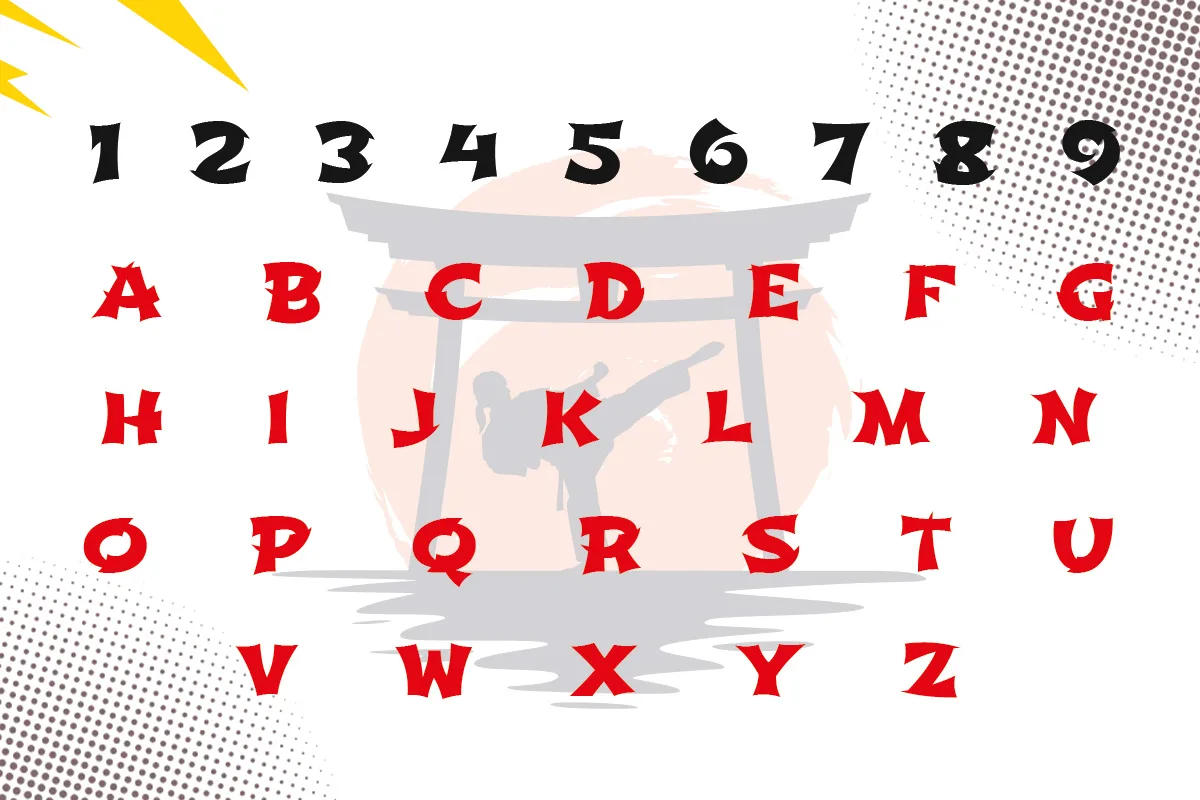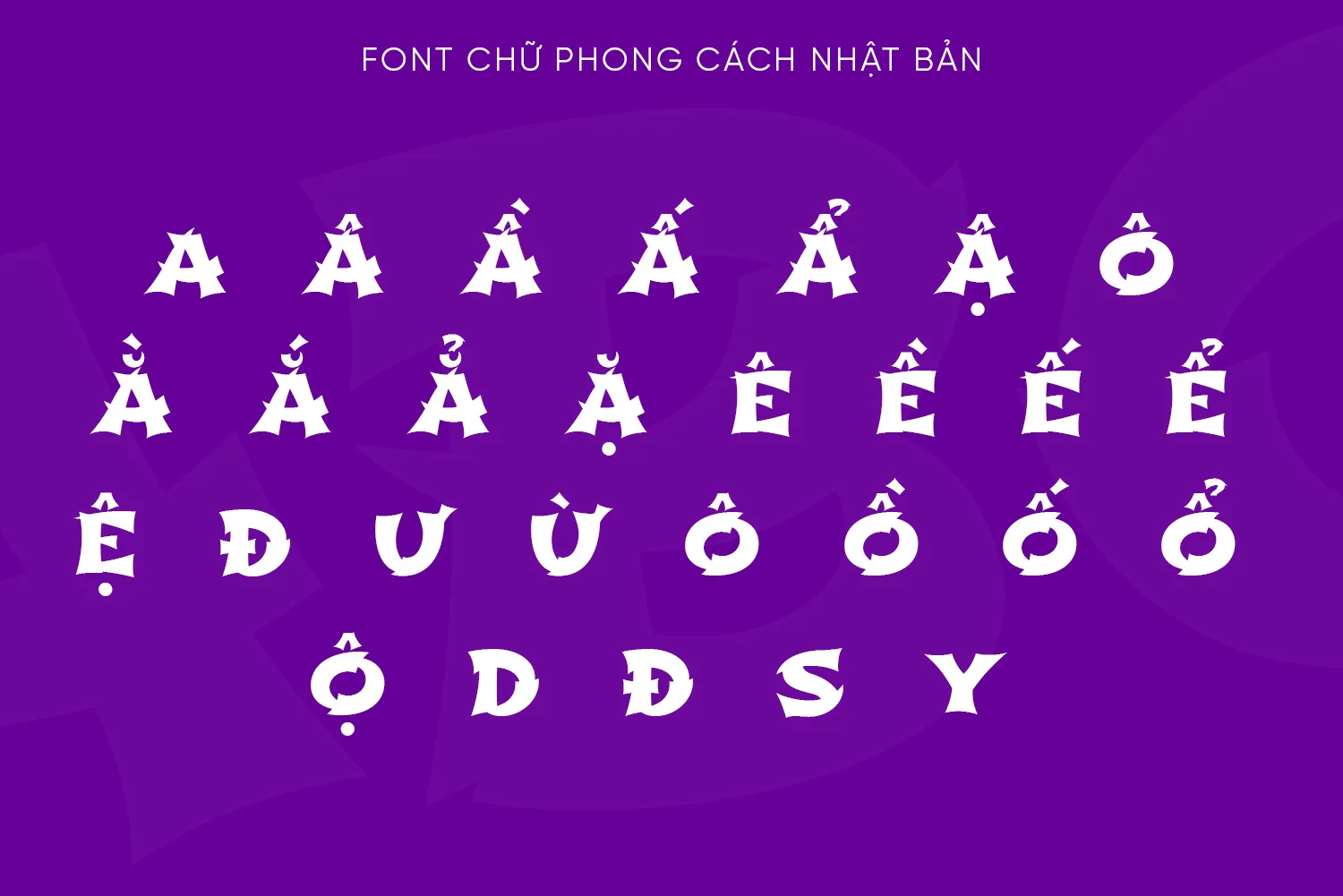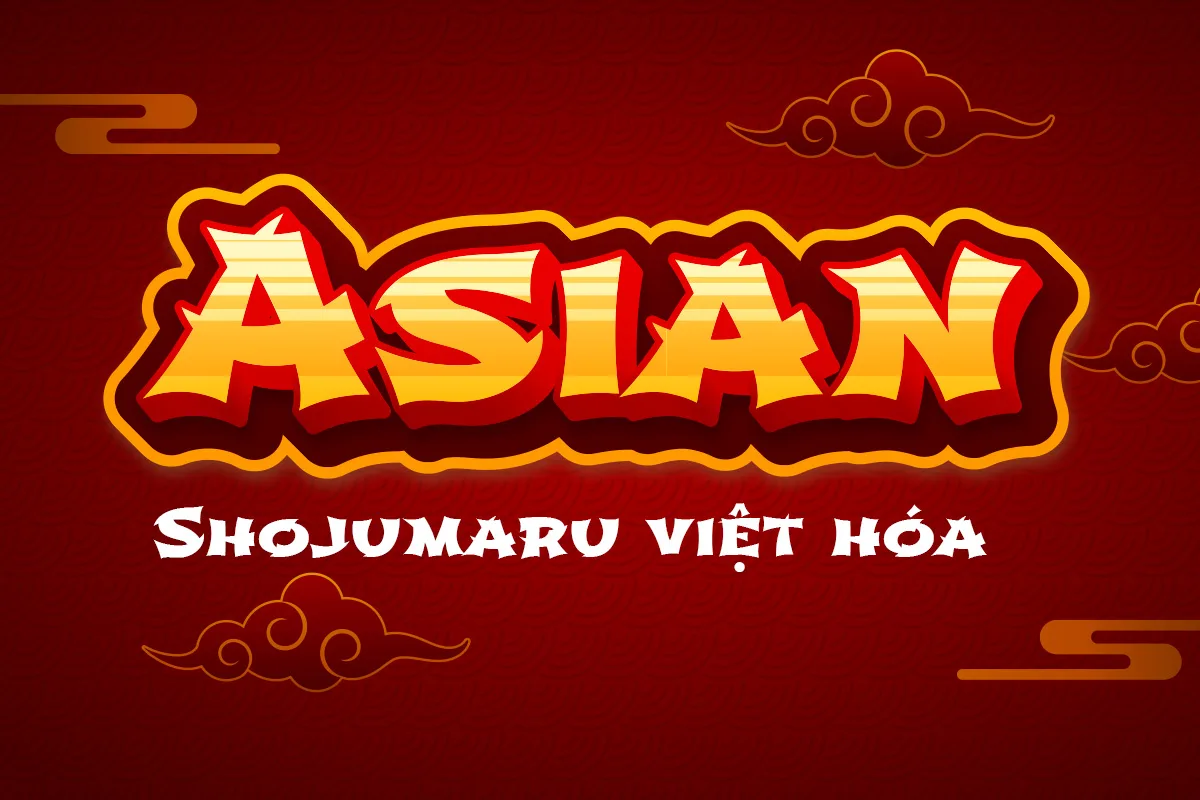
DVN Shojumaru Việt hóa – Font chữ phong cách karate đậm chất Nhật Bản
DVN Shojumaru Việt Hóa là kiểu chữ mang đậm chất Á Đông với phong cách vẽ tay táo bạo và đường nét mạnh mẽ. Font tạo cảm giác cổ điển, hoài niệm, gợi nhớ đến những nét bút thư pháp cách điệu, rất phù hợp cho các thiết kế mang chủ đề võ thuật, truyện tranh, phim ảnh, game hoặc tiêu đề quảng cáo cần sự nổi bật. Các ký tự được thiết kế có cấu trúc đặc trưng, tạo nên điểm nhấn mạnh mẽ trong từng con chữ. Phiên bản Việt hóa được tối ưu tỉ mỉ để hỗ trợ đầy đủ bảng chữ cái tiếng Việt, đảm bảo sự đồng nhất và thẩm mỹ cao. DVN Shojumaru không chỉ là một font chữ, mà còn là lựa chọn lý tưởng để thể hiện cá tính và chiều sâu văn hóa trong các thiết kế hiện đại mang cảm hứng truyền thống.